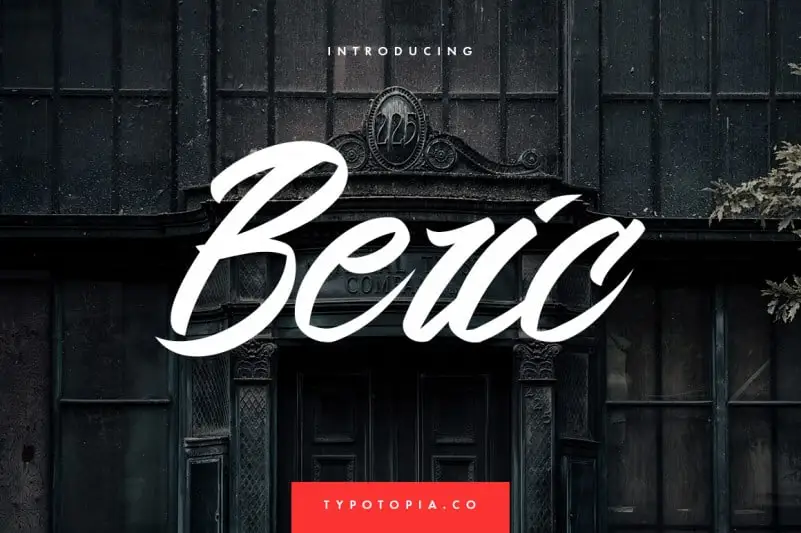
Beric Script Font – Download Grátis
A fonte Beric Script Font inspira-se nas tipografias clássicas, trazendo seu próprio estilo único para qualquer projeto de design. Essa fonte a mão desenhada é perfeita tanto para headlines de diferentes tamanhos quanto para textos de bloco que podem ter variações muito grandes e pequenas. Através da Beric Script Font, você pode criar designs assustadoramente boho – seja para web, impressão, imagens em movimento ou qualquer outro projeto. Suas formas elegantes e suaves permitem que o texto se adapte ao seu projeto de forma atraente e harmoniosa. Com a Beric Script Font do designer typotopia, você terá uma ferramenta poderosa para expressar seu estilo pessoal e personalizar sua identidade visual de maneira única. Ela é ideal tanto para designers profissionais quanto para aqueles que estão aprendendo no caminho, proporcionando liberdade criativa sem comprometer a estética elegante e sofisticada do design moderno. Adquira agora a Beric Script Font typotopia, e deixe sua marca com um toque de boho sophistication.